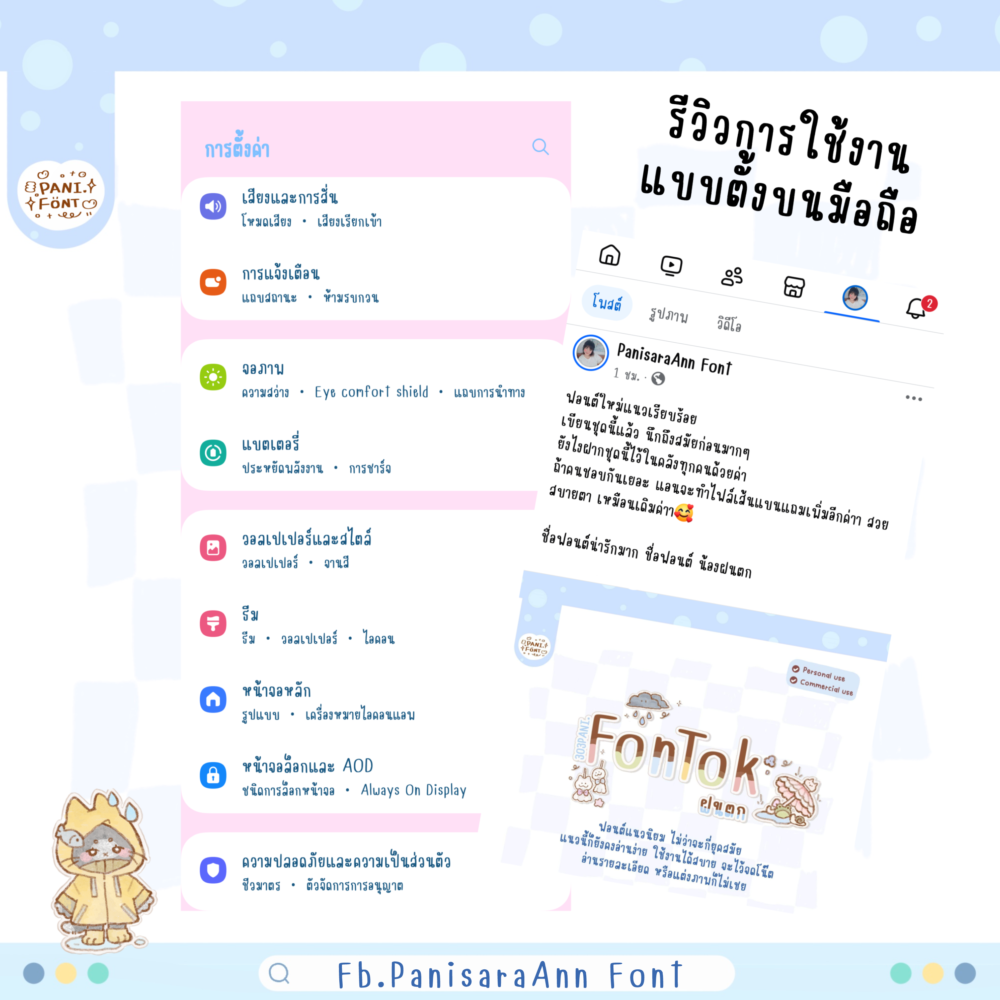
ฝนตก
ฟอนต์แนวเรียบร้อย เขียนชุดนี้แล้ว นึกถึงสมัยก่อนมากๆ
แอนทำไฟล์เส้นแบนแถมเพิ่มอีกไฟล์ค่ะ
สวย สบายตา เหมือนเดิมค่าา
ชื่อฟอนต์น่ารักมาก ชื่อฟอนต์ น้องฝนตก